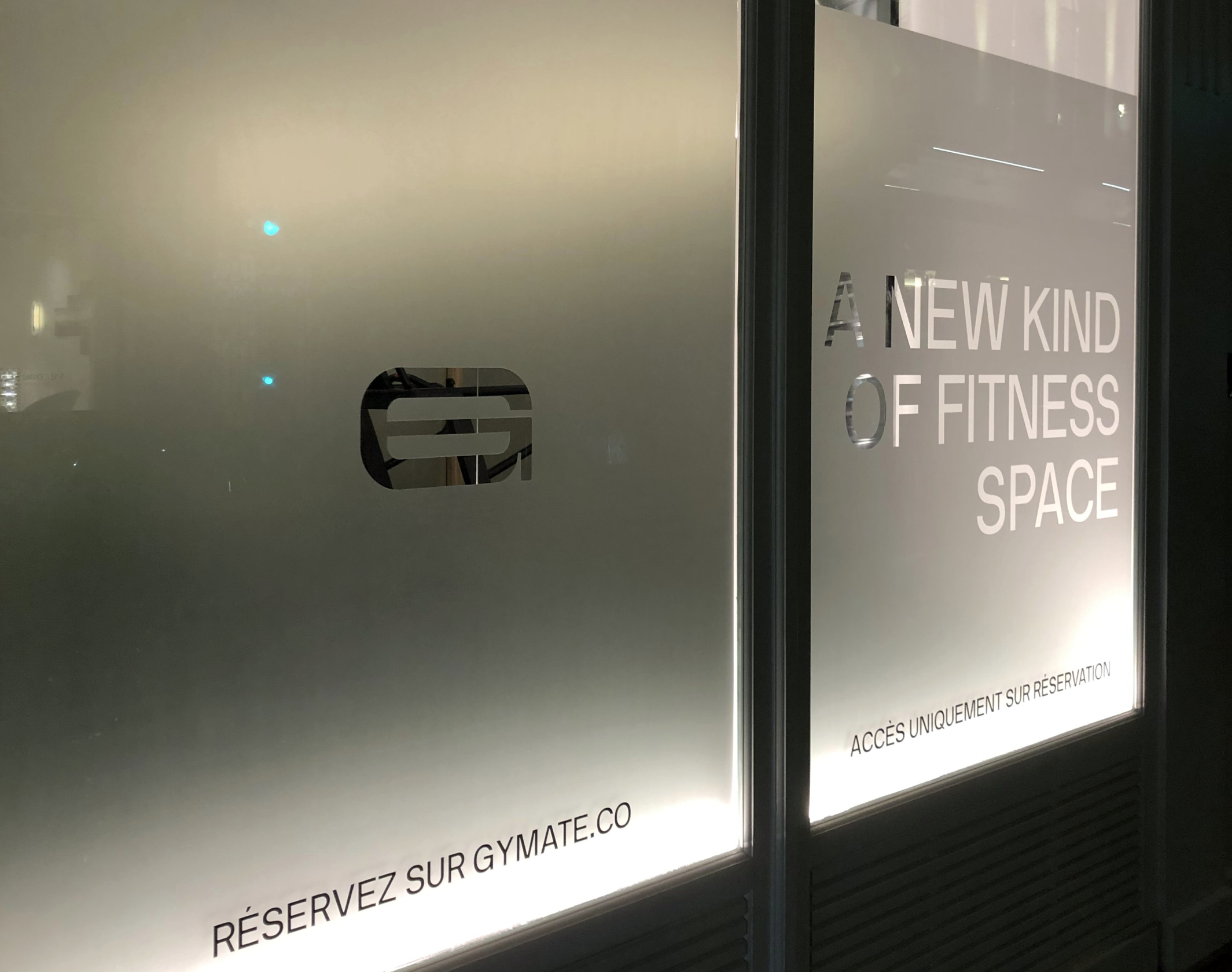
Gymate
Gymate révolutionne le fitness privé à Paris avec une identité graphique dynamique et raffinée, prête à conquérir l'Europe
Gymate, dont le premier lieu a ouvert en février 2022 à Paris (3e arrondissement), sont les premiers espaces privés de fitness, entièrement équipés, disponibles à la demande. Destinés à des clients désireux de s’entraîner seuls, avec un coach ou entre amis, ces espaces raffinés et confidentiels, dont l’architecture a été conçu par le studio DAS, sont amenés à se développer en France et en Europe. Brand Brothers a été appelé pour développer l’identité graphique et le système visuel.
Nous avons conçu un typogramme sur la base de caractères géométriques à chasse très étendue, dotés d’inktraps prononcés. Le ‘G’ a la particularité d’être totalement refermé en son centre. Cet étirement exagéré des caractères, évoquant le mouvement et l’effort, se retrouve dans le système visuel, où l’initiale de Gymate se décline en différentes largeurs, formant la base d’un système graphique brut dynamique. L’ensemble est associé au caractère NB National (Neubau, Berlin), et une palette colorimétrique réduite. Les premières déclinaisons ont été appliquées sur des séries de posters, l’environnement digital et sur la signalétique du premier espace, rue Saint Martin.